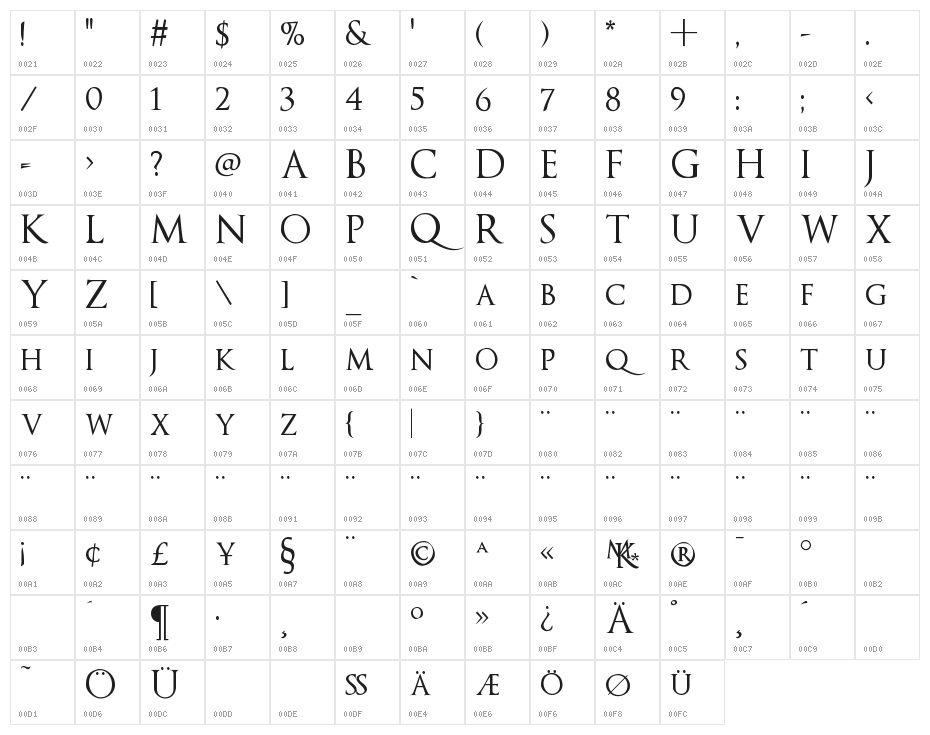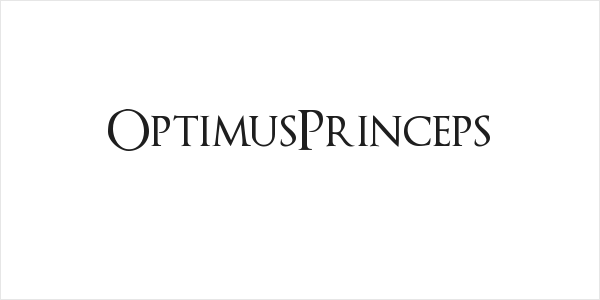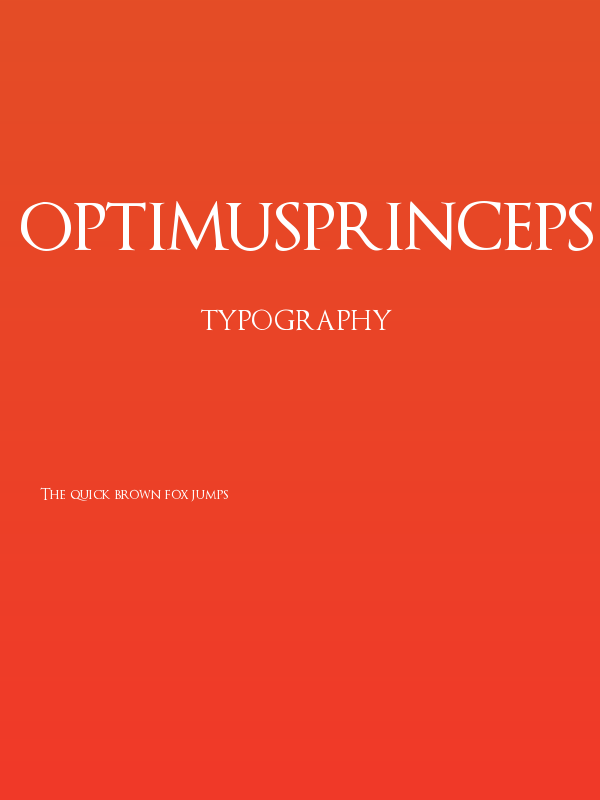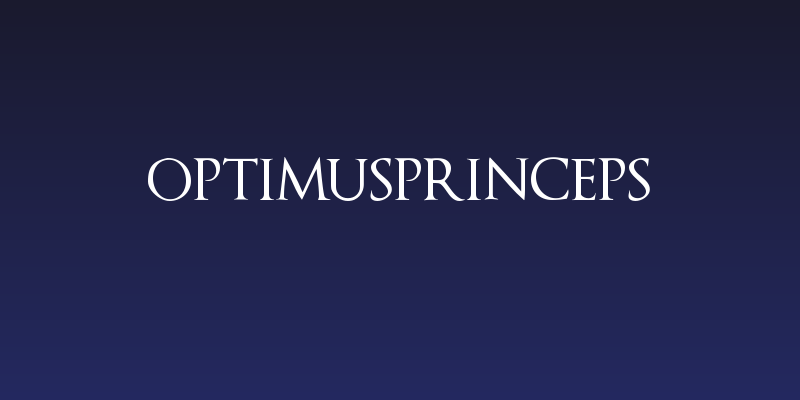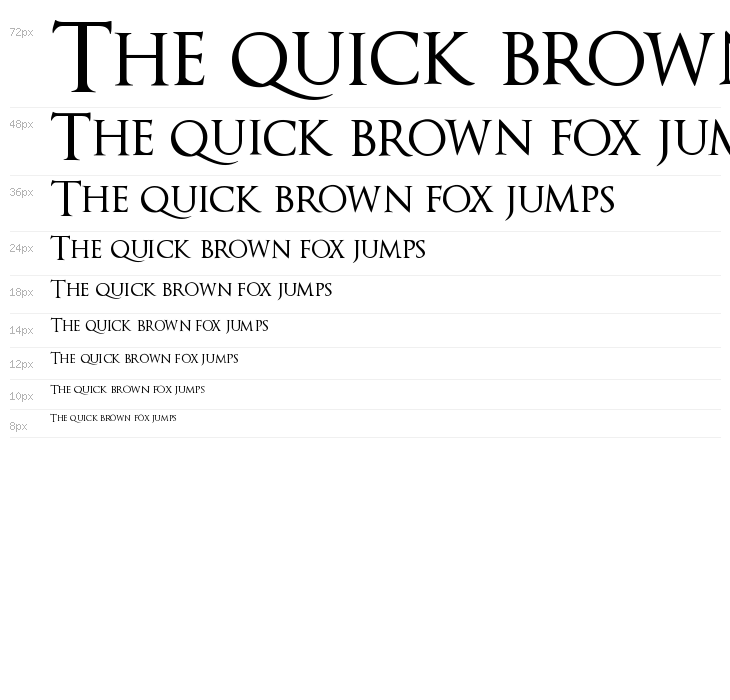
OptimusPrinceps Font
✎ Serif
| Gesamtstil | Classic |
| Anwendungsfall | Headlines, Body text, Logos |
| Vorgeschlagene Projekte | Ideal for projects requiring a historical or formal touch, such as book covers, certificates, or branding for luxury products. |